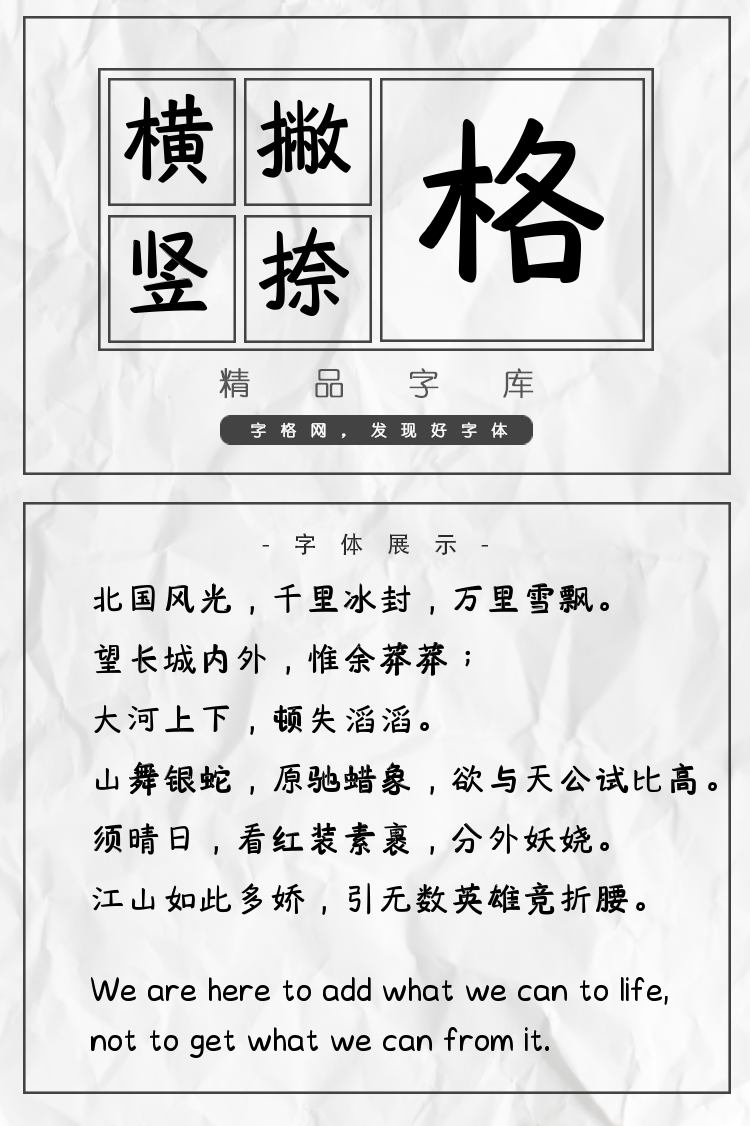
也字工厂瑞云浓楷书
字体说明:也字工厂瑞云浓楷书字体是一款可商用的毛笔书法,英文手写,手写体字体,该字体包含6763个中文、字母、符号和数字,具有充满力量、大气、豪放、稳重、手写风、古典 的风格,可以满足您设计上的各种需求,该字体主要用于电商、广告、视频影视、海报企宣、书籍 等场景, 您不但可以在字格网下载也字工厂瑞云浓楷书,同时还有众多毛笔书法字体、创意字体等可供选择!